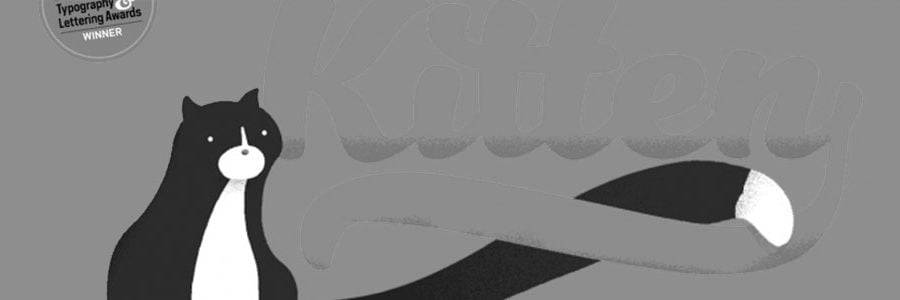
La typographie gratuite Kitten nous fait des yeux de chat !
KITTEN: Typographie gratuite originale
Kitten est une famille de caractères multi-poids avec une large gamme de variantes, de suppléments et de ligatures conçues par Cosimo Lorenzo Pancini, avec des dingbats de chat conçus par Isabella Ahmadzadeh.
Kitten curvy, ce sont des caractères en gras dont le poids régulier est parfait pour la conception de logo et l’utilisation de l’affichage, tandis que les poids plus propres et plus clairs, ainsi que la version Monoline et la variante condensée de Slant, sont parfaites pour des blocs de texte plus longs.
Kitten couvre plus de 40 langues qui utilisent l’alphabet latin, avec une gamme complète d’accents et de diacritiques.
Cette typo est disponible en cinq poids et dispose de trois variantes de style: Regular, Slant et Swash. Kitten utilise pleinement les ligatures Open Type pour éviter les conflits de lettres en majuscule et fournir des variantes et un large éventail de caractères de ligature pour un aspect naturel plus fait à la main.
On peut accéder à Swash via une palette de glyphe ou en tapant un à six caractères de soulignement après la lettre. Un espace suivi de un à huit caractères de soulignement produit différentes silhouettes de chat.
Cette typographie est parfaite pour vos créas sur des affiches aux grands formats, des brochures, les logos et la décoration graphique mais aussi pour les cartes de visite originales.